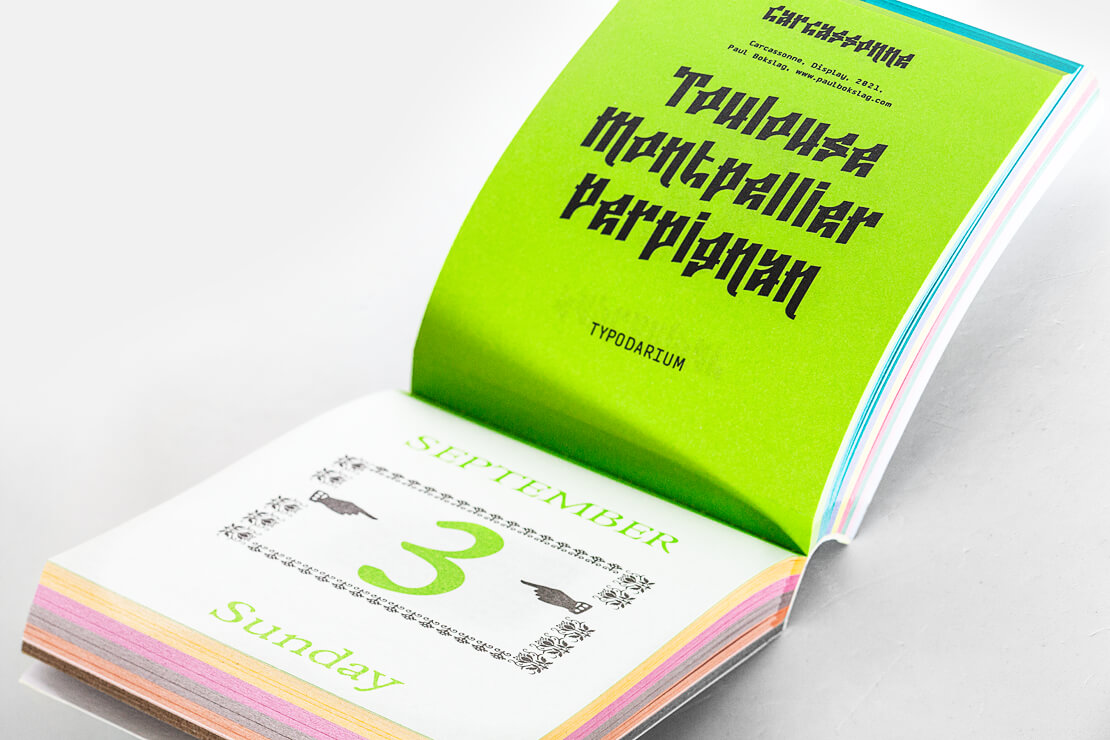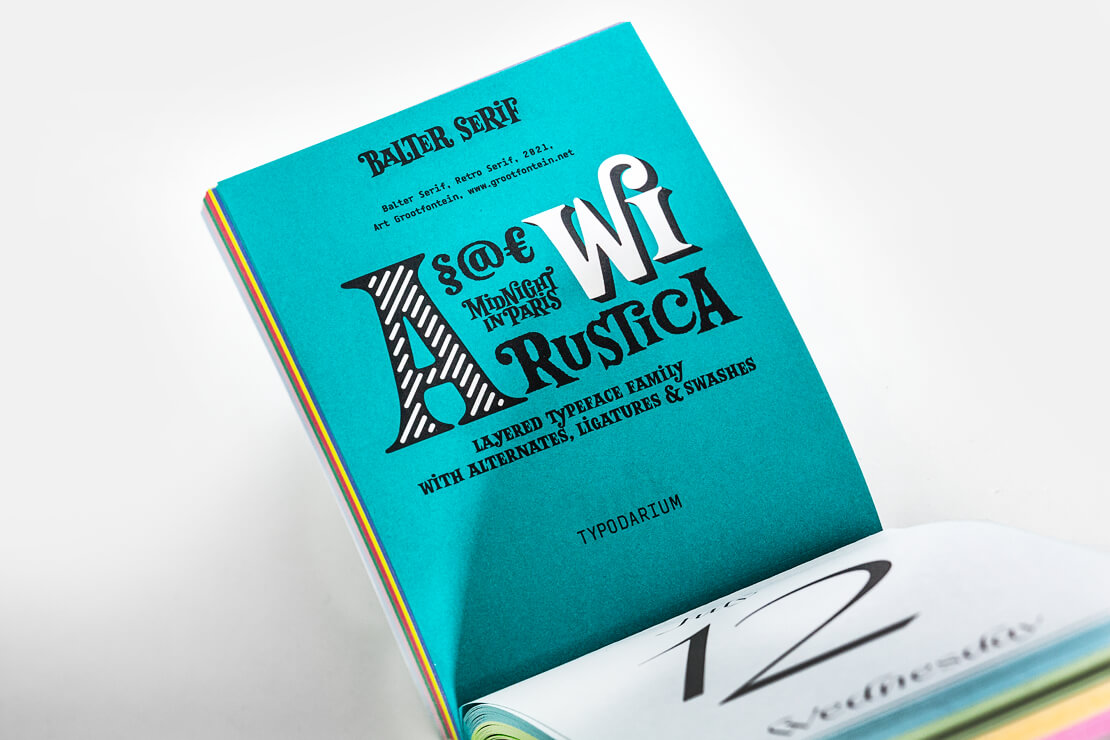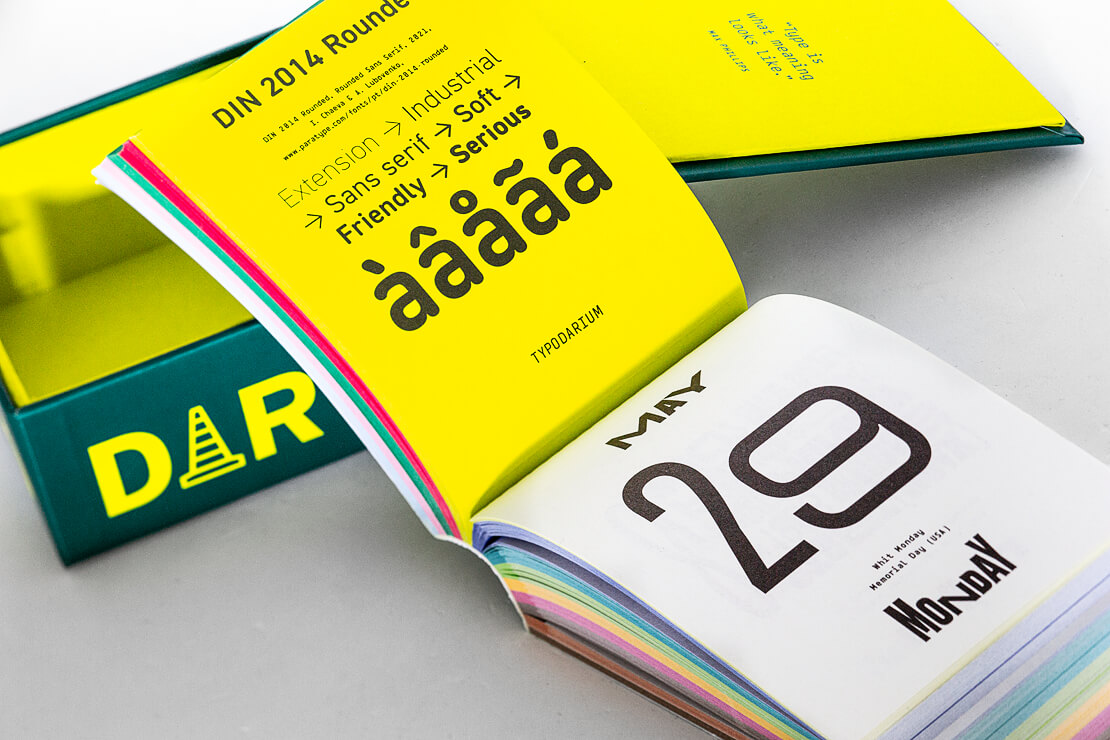
Typodarium 2023: Typografischer Abreißkalender
Das »Typodarium 2023« ist da. Raban Ruddigkeit und Lars Harmsen präsentieren in diesem typografischen Abreißkalender 365 inspirierende Schriften für das kommende Jahr.
Die neueste Ausgabe für das Jahr 2023 zeigt sich in 12 fröhlichen Farben. Tag für Tag gibt es im Typodarium eine neue Schriftart zu entdecken. Der neue Kalender kommt auf insgesamt 365 Schriften von 236 Kreativen aus 34 Ländern.
Auf den Tagesblättern sind jeweils Angaben zu Datum, Wochentag und ggf. auch Feiertag enthalten. Die Rückseiten präsentieren die zum Einsatz gekommenen Schriftarten. Zudem findet man dort auch noch weitere Informationen zum Kreativen, dem Entwicklungsjahr sowie etwaige Bezugsmöglichkeiten.
Frische, kreative Schriftarten im Typodarium 2023 Kalender
Im Typodarium 2023 gibt es viel zu entdecken. Neben Trendschriftarten haben es auch Brotschriften, Lese- und Zierschriften sowie Handgemachtes in den Kalender geschafft.
Die mitgelieferte Sammelbox erweist sich als praktisch. Dort lassen sich die abgerissenen Kalenderseiten aufbewahren. Auf diese Weise kann aus dem Typodarium 2023 ein ganz persönliches Musterbuch mit eigenen Schriften-Highlights werden.